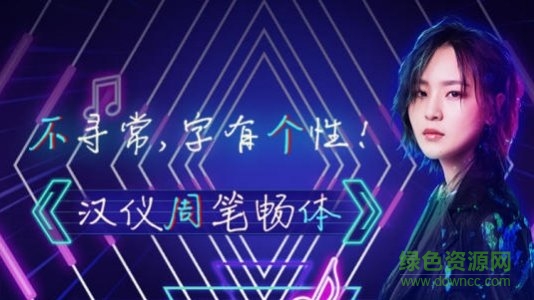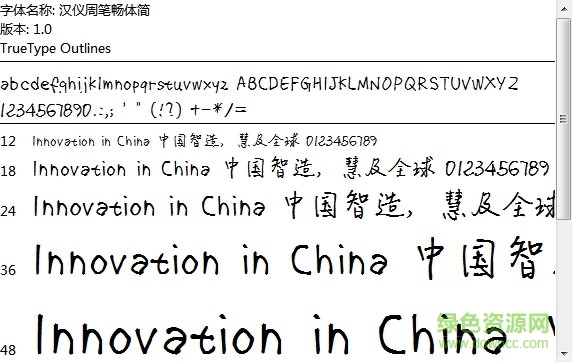
漢儀周筆暢體
漢儀周筆暢體ttf是漢儀字庫專為歌星周筆暢打造的個性字體,字跡流暢非常,有著獨特的視覺呈現(xiàn),如同與筆筆一起聊天對話,快來綠色資源網(wǎng)搶先感受一下吧!
漢儀周筆暢體 華為字體特色
眷筆一生,傾暢一世。愛你,筆時光更暢久。漢儀周筆暢體,不尋常,字有個性!
字體點評
漢儀周筆暢體氣韻流暢,健勁清峻,眼前又浮現(xiàn)起了周老板伏案一筆一劃寫正楷的身影~即刻下載,讓周筆暢為你“代書胸臆”!這回可是real“文筆流暢”了!